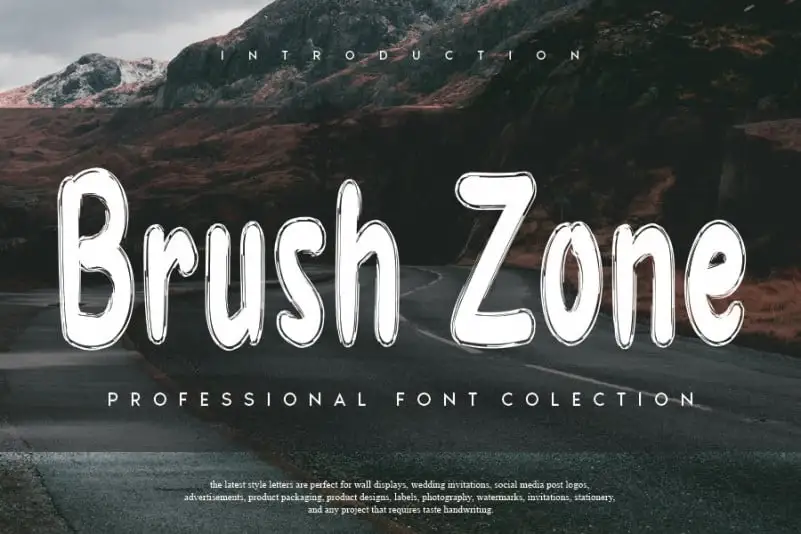
Brush Zone Brush Font – Fonte Grátis
Brush Zone Brush Font
A Brush Zone Brush Font é uma fonte escrita a mão casual com um toque único criada com o auxílio de um canivete de pintura. Esta fonte tem um estilo limpo e um toque um pouco desafiador, que complementará perfeitamente todos os seus logotipos, marcasigns, projetos em mídia social e trabalhos DIY práticos. Perfeita para designers digitais e criadores de conteúdo, a Brush Zone Brush Font é uma escolha inteligente para aqueles buscando um estilo único que se destaca em qualquer projeto. Não importa o tamanho do seu projeto ou o formato, este script font é uma maneira elegante de dar vida aos seus projetos.